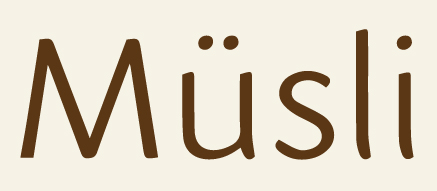
Schrift von Verpackung gesucht
ich suche diesen Font (siehe angehängtes Foto).
Hab es schon mit diversen Identi-Webseiten und Suchen probiert.
Die FF Enzo käme sehr nahe, ist aber eckiger. Wenn der Screenshot einem pdf entspringt, könntest du dort in den Eigenschaften nachschauen.
ja, es kommt aus einem PDF. Allerdings ist genau dieses eine Wort in Pfade umgewandelt und daher nicht in den Eigenschaften zu finden.
Stimmt, die Enzo geht schon in die Richtung. Ich brauch leider für den Nachbau genau den gleichen Font.
Wenn du das gesamte pdf zur Verfügung stellst, könnten wir weiter forschen …